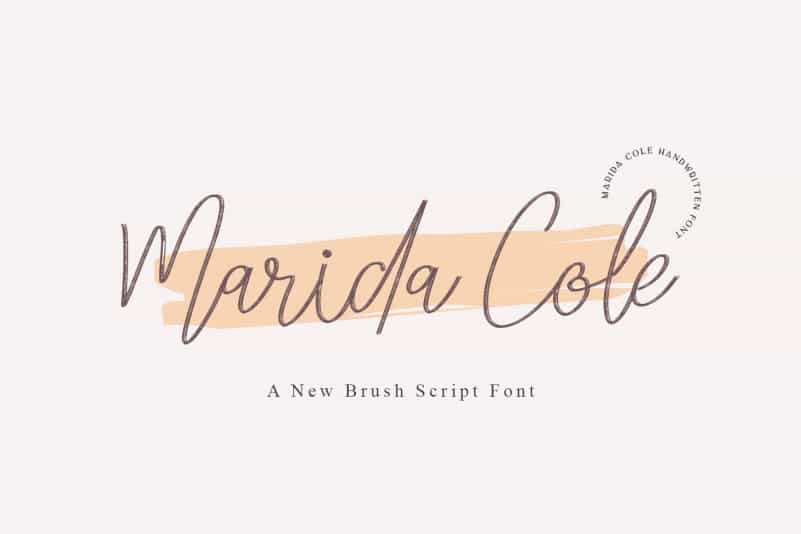
Marida Cole Script Font – Fonte Grátis
Marida Cole Script Font
A Marida Cole Script Font é uma elegante tipografia escrita a mão que oferece beleza e equilíbrio. Desenvolvida para os designers com criatividade, esta tipografia delicada e suave se adapta perfeitamente a um vasto número de projetos. Excelente para branding, logotipia, design wedding, postagens nas redes sociais, anúncios, embalagens de produtos, designs de produtos, etiquetas, fotografia, marcas de água e convites, ela se destaca em qualquer projeto. Com sua delicadeza e harmonia entre as letras, esta fonte é uma escolha inteligente para quem procura um estilo único e atraente que se adapta facilmente a vários tipos de projetos gráficos. Experimente a Marida Cole Script Font para transformar seus designs em obras de arte inovadoras.